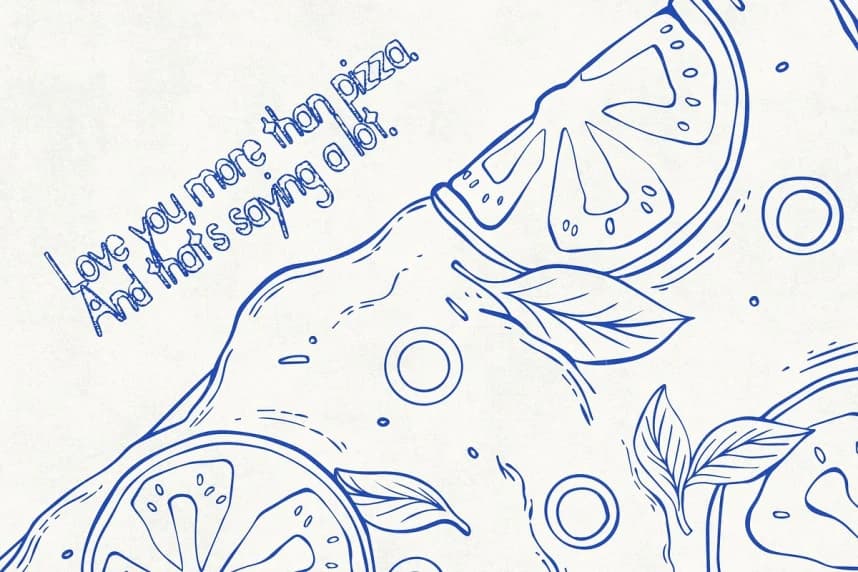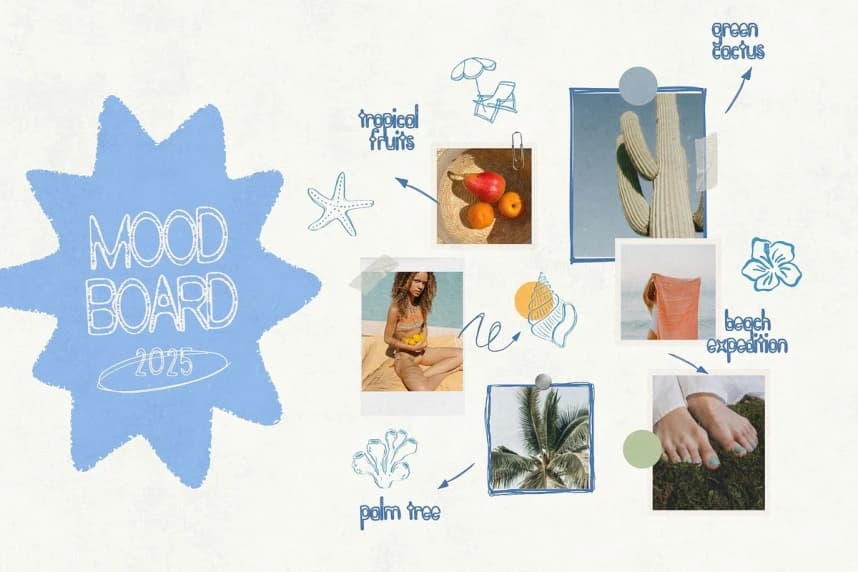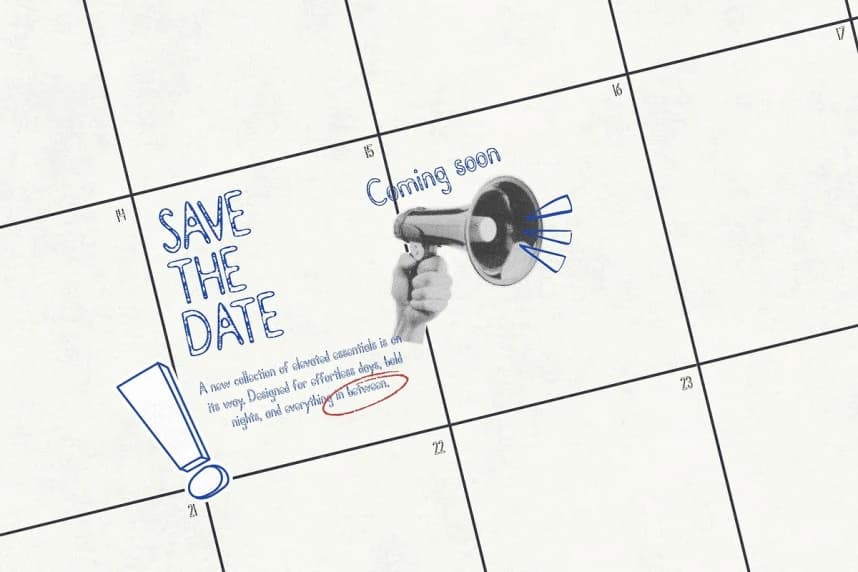
Quirkstroke Playful Yazı Tipi
Quirkstroke Playful Font, el yapımı, eskiz stilinde kontur yazı tipi; grunge görünümlü, aşınmış bir çekiciliğe sahip. Kendini çok ciddiye almayan projeler için mükemmel olan bu font, benzersiz, el yapımı bir dokunuşu korurken çocukça bir oyun hissini de bünyesinde barındırır.
Quirkstroke Playful Yazı Tipi, el yapımı, eskiz tarzı kontur bir yazı tipidir ve grunge görünümlü, aşınmış bir çekiciliğe sahiptir. Kendini çok ciddiye almayan projeler için mükemmeldir; bu yazı tipi çocukça bir oyun hissi taşırken benzersiz, el yapımı bir dokunuşu da korur.